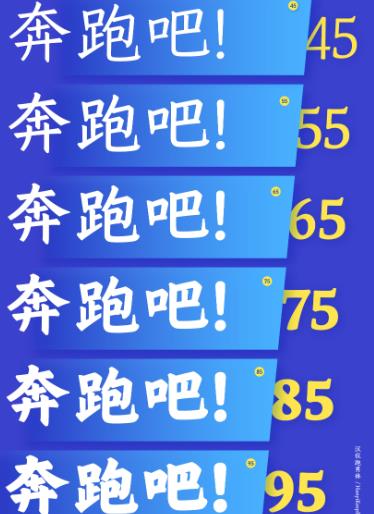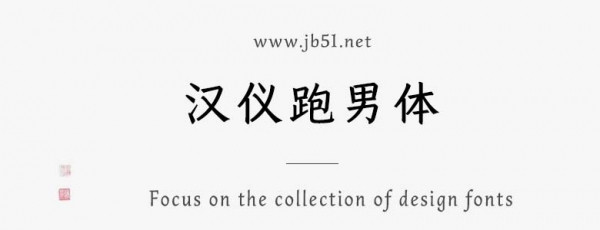
漢儀跑男體家族由漢儀字庫出品的藝術字體,端正大方,簡潔均衡,同時兼具動感活力??瑫鵀闀ㄖ#?個字重,通過不同的字重可以滿足不同視覺層級的排版需求,適用于廣泛的字體使用場景,具有很好的視覺感,適合應用于藝術設計、平面宣傳設計、網頁設計,書法字帖等領域。有需要的朋友快來本站下載使用吧。
漢儀字庫與《奔跑吧》節(jié)目組聯(lián)合推出國內首款綜藝 IP 字體——漢儀跑男體?;诠?jié)目的青春活力和娛樂精神,以字庫技術賦能節(jié)目煥新,建立獨特的視覺印象。既能兼顧傳統(tǒng)的書法之美呈現(xiàn)于節(jié)目中,又符合現(xiàn)代應用的普適性;能夠傳達出節(jié)目中活力拼搏的歡樂氛圍,契合綜藝節(jié)目的年輕化、潮流感,具備廣泛的受眾吸引力。
漢儀跑男體是一套綜藝楷體家族字體,端正大方,簡潔均衡,同時兼具動感活力。楷書為書法之楷模,將其周正之美展現(xiàn)在《奔跑吧》節(jié)目之中,彰顯文化底色。
字形穩(wěn)健端正,結構嚴謹均衡,筆畫造型凝練概括,具備現(xiàn)代幾何之美。
家族規(guī)劃共6個字重,通過不同的字重可以滿足不同視覺層級的排版需求,適用于廣泛的字體使用場景,例如綜藝海報、節(jié)目字幕、廣告宣傳、社交媒體等。
取法顏真卿和柳公權的楷書,筆意可見顏筋柳骨,繼承書法基因,骨力遒勁,剛中帶柔。
漢儀跑男體的西文,參考人文主義風格,將中文的特色很好地結合在其中,實現(xiàn)中西文的高度匹配。并強化結合圖形感,兼具手寫斜勢筆意和印刷雕刻痕跡,增強視覺表現(xiàn)力。